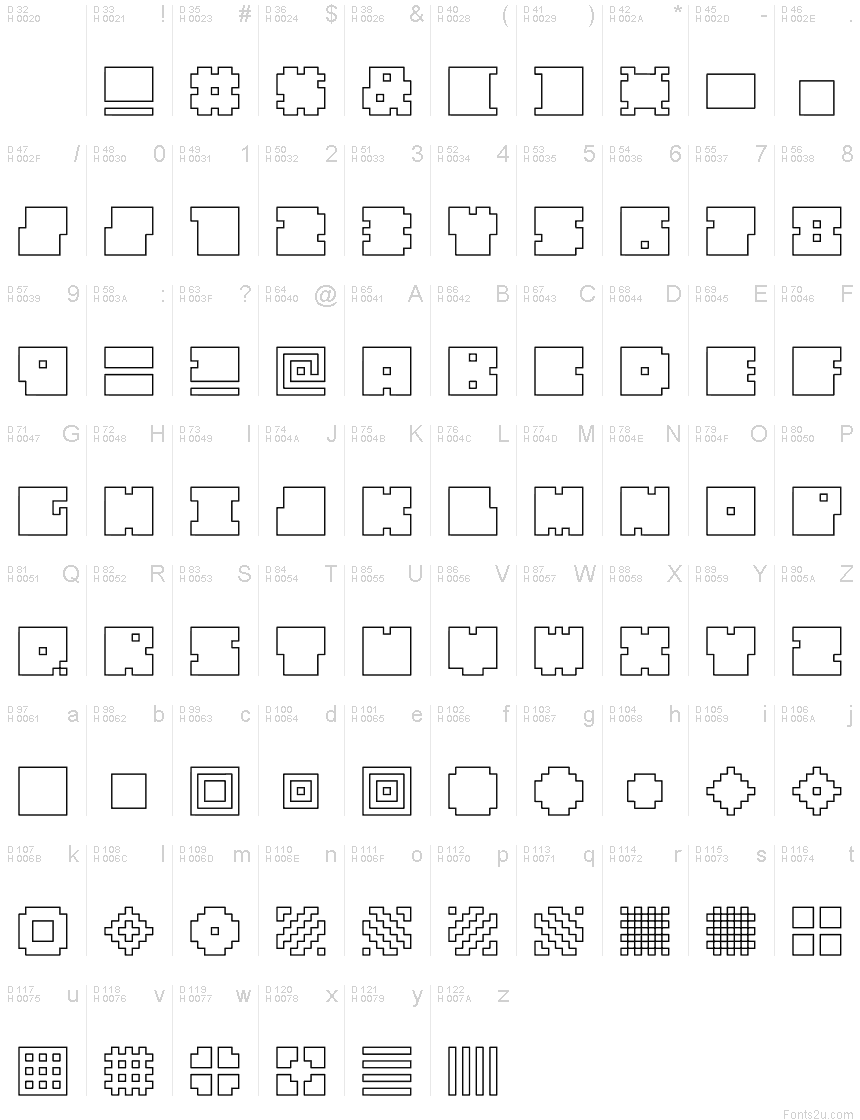
Qube Hollow autorstwa Dana Reddinga z B/W Fontworks to darmowy, konturowy krój displayowy techno, zbudowany z szerokich, kwadratowych wielkich liter. Prostokątne cięcia i małe wewnętrzne nacięcia nadają literom mechaniczny profil. Formy są surowe i zwarte konstrukcyjnie.
Motywy technologiczne i z gier arcade pasują do jego pudełkowej geometryczności, co czyni go przydatnym do grafiki w grach, plakatów muzyki elektronicznej, opakowań w stylu science-fiction, oznakowań imprez i wizualizacji scenicznych. Jego puste, modułowe litery przypadną do gustu przede wszystkim projektantom pracującym z retrofuturystyczną rozrywką i przemysłową estetyką.